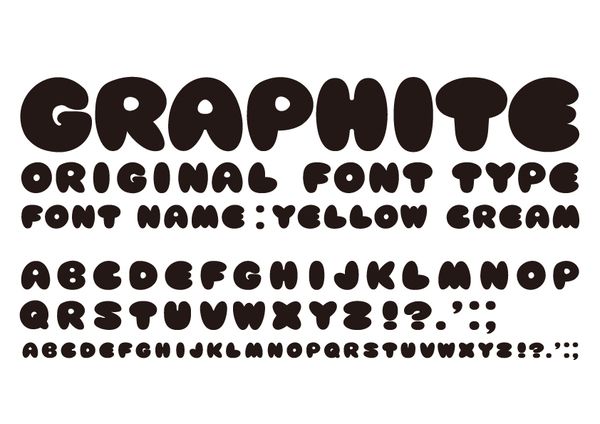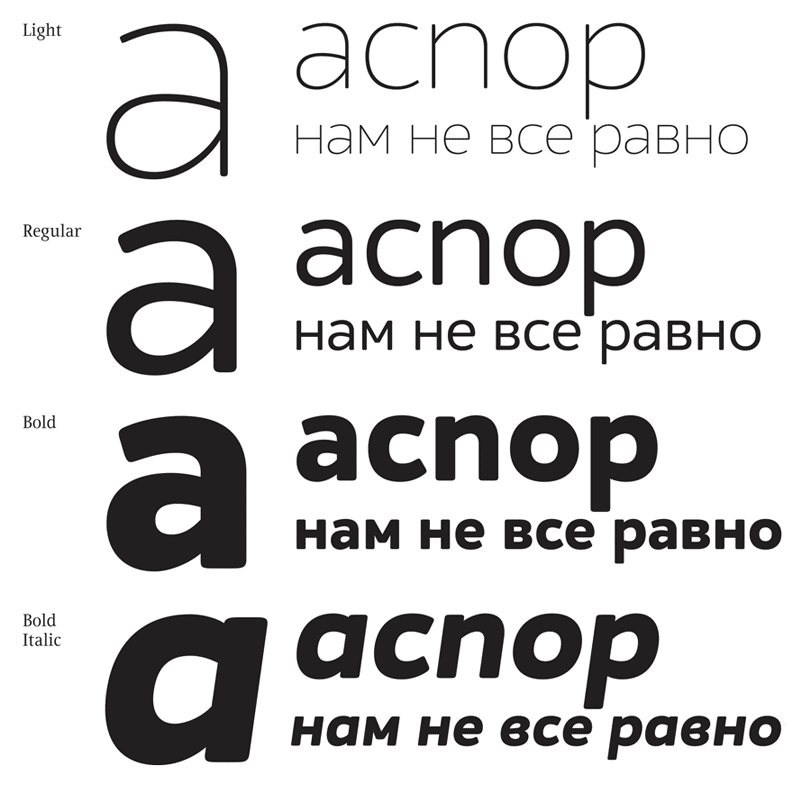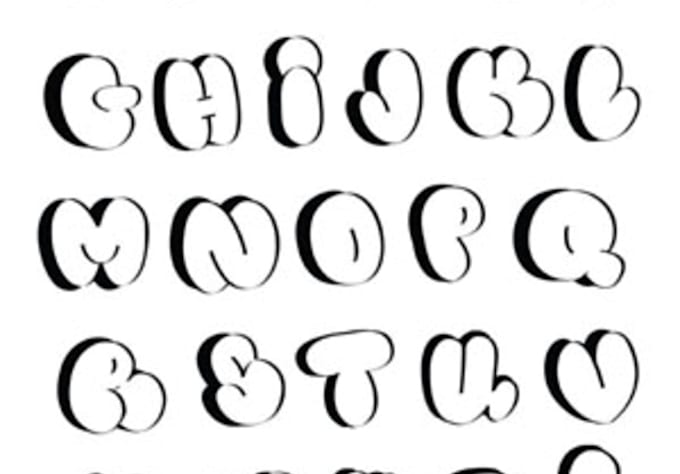
20+ скругленных шрифтов
Закругленные шрифты обычно используются в креативном дизайне, чтобы добавить немного элегантности и стиля заголовкам и заголовкам. Они также являются отличным выбором для текста абзаца, поскольку улучшают читаемость.
Вы можете использовать округлые шрифты практически для любого дизайна. В том числе для создания логотипов, заголовков плакатов, листовок, заголовков веб-сайтов или даже дизайнов футболок. Они просто делают любой дизайн более стильным.
Если вы ищете отличный шрифт с закругленными углами для своего проекта, вам повезло.
В этой коллекции мы демонстрируем одни из лучших бесплатных и бесплатных закругленных шрифтов, которые вы можете использовать в своих проектах. Обязательно скачайте их все.
Espion Rounded
Espion — еще один современный шрифт с закругленными буквами. Он также отличается очень четким дизайном букв, что делает его подходящим для многих различных типов проектов. Шрифт включает как прописные, так и строчные буквы.
Alma Sans
Этот округлый шрифт отличается ультратонким дизайном с низким уровнем контрастности и современным минималистичным дизайном букв. Это поможет вам создавать чистые и простые названия, особенно для стартапов и креативных агентств.
Relica Trio
Relica — это прекрасное семейство шрифтов, которое включает три разных стиля, включая ретро и контурный дизайн. Этот шрифт идеально подходит для создания всего, от заголовков плакатов до логотипов и этикеток. Он также включает версии веб-шрифтов.
Mint Round
Это многослойный, зеркальный, округлый шрифт, который вы можете использовать для придания поистине уникального внешнего вида своим дизайнам. Этот шрифт может не подходить для всех типов дизайна, но он, безусловно, поможет персонализировать ваши заголовки и заголовки.
Grand Halva
Как и его название, Grand Halva — это шрифт с великолепным дизайном. Он отличается элегантным стилем закругленных букв, который будет потрясающе смотреться с роскошным дизайном брендов.
Вы можете использовать его для создания названий, логотипов, значков и многого другого.
Rotterdam
Этот бесплатный шрифт также имеет ретро-винтажный дизайн. Высокие сжатые буквы придают ему еще более привлекательный вид. Вы можете бесплатно использовать это в своих личных дизайнерских проектах.
Phalang
Это уникальный округлый шрифт с буквенным дизайном в стиле ретро. Все в этом шрифте напоминает ретро, и он идеально подходит для создания названий для музыкальных плакатов и листовок. Его можно использовать в личных проектах.
Nordin Rounded
Nordin — красивый округлый шрифт с сокращенным стилем букв. Высокий и узкий дизайн букв делает этот шрифт идеальным выбором для создания жирных заголовков для плакатов и баннеров. Это шрифт, состоящий только из заглавных букв, с лигатурами, цифрами и многоязычной поддержкой.
Alumatica
Этот элегантный шрифт без засечек имеет гладкий дизайн с закругленными буквами, который обязательно привлечет внимание вашей аудитории.
Шрифт идеально подходит для роскошного бизнеса и высококачественного брендового дизайна. А также дизайн заголовков в социальных сетях и веб-сайтах.
George Round
С первого взгляда можно увидеть, как замечательно этот шрифт будет смотреться в дизайне заголовка веб-сайта. Он также идеально подходит для создания заголовков и заголовков для социальных сетей и плакатов. Специально для делового и профессионального дизайна. Шрифт доступен в 8 вариантах начертания, от светлого до жирного.
Nubolts
Он большой, жирный, все заглавные, Nubolts — это шрифт, который вы захотите создать для гигантских заголовков для своих проектов. Он имеет несколько округленных стилей шрифта и веса, включая обычные и контурные версии. Шрифт также включает многоязычную поддержку.
Pulsar
Этот бесплатный шрифт идеально подходит для дизайна плакатов и флаеров. Он имеет футуристический дизайн букв с закругленными краями. Шрифт можно использовать в личных или коммерческих проектах.
Lucy Rounded
Еще один элегантный округлый шрифт с геометрическим рисунком. Этот шрифт доступен в нескольких вариантах толщины и стиля, включая курсив и даже версии веб-шрифтов. Он также имеет расширенную многоязычную поддержку для создания дизайнов, ориентированных на международную аудиторию.
Polly Rounded
Polly — это современный округлый шрифт с минималистичным дизайном. Простота дизайна букв делает этот шрифт наиболее подходящим для дизайна, связанного с современным бизнесом, таким как стартапы и корпоративные агентства.
Nano
Еще один бесплатный шрифт с закругленными буквами. Этот шрифт имеет очень минималистичный дизайн с футуристическими элементами. Этот шрифт можно использовать бесплатно в личных и коммерческих проектах.
Story Telling
Это бесплатный шрифт с закругленными углами, который вы можете использовать в своих личных проектах. Он отличается очень непринужденным и забавным дизайном, что делает его отличным выбором для создания названий для школьных и детских проектов.
Круглые гарнитуры, также называемые гарнитурами закругленный, Они являются частью стиля без засечек и, допустим, являются еще одним из стилей, которые являются частью того, что мы знаем как семейства шрифтов. В этом посте мы собираемся объяснить, что они собой представляют и какие функции они выполняют своим дизайном или индивидуальностью.